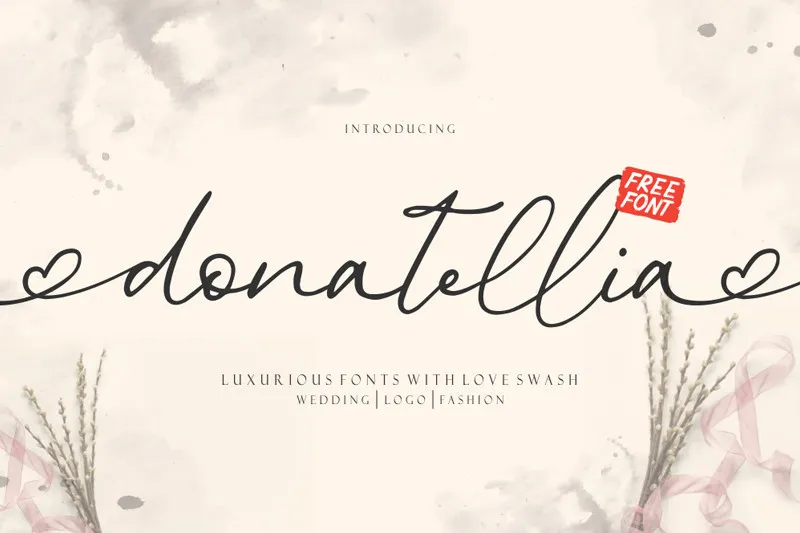
Donatellia Signature Font – Download Grátis
Descubra uma nova opção para suas criações digitais com a Donatellia Signature Font do designer 24Design. Essa é uma fonte script que se destaca por sua elegância e criatividade, perfeita para usar nas camadas mais sofisticadas de seus projetos. Este singular recurso gratuito inclui Donatellia Signature Font em formatos OTF, TTF e WOFF, acompanhado de ligaturas e recursos da abertura do tipo aberto. Além disso, oferece uma coleção de conjuntos estilísticos que incluem carinhas apaixonadas para finalizar ou começar sua escrita. Perfeita para logos, cartas de casamento, posteres, cards empresariais, cabeçalhos, histórias no Instagram e YouTube, capas de livros e promoções de propaganda. A Donatellia Signature Font é uma fonte que não apenas adicionará um toque único a seus trabalhos, mas também dará vida aos seus projetos digitais. Descubra o poder da Donatellia Signature Font hoje e deixe seu design se destacar entre a multidão.